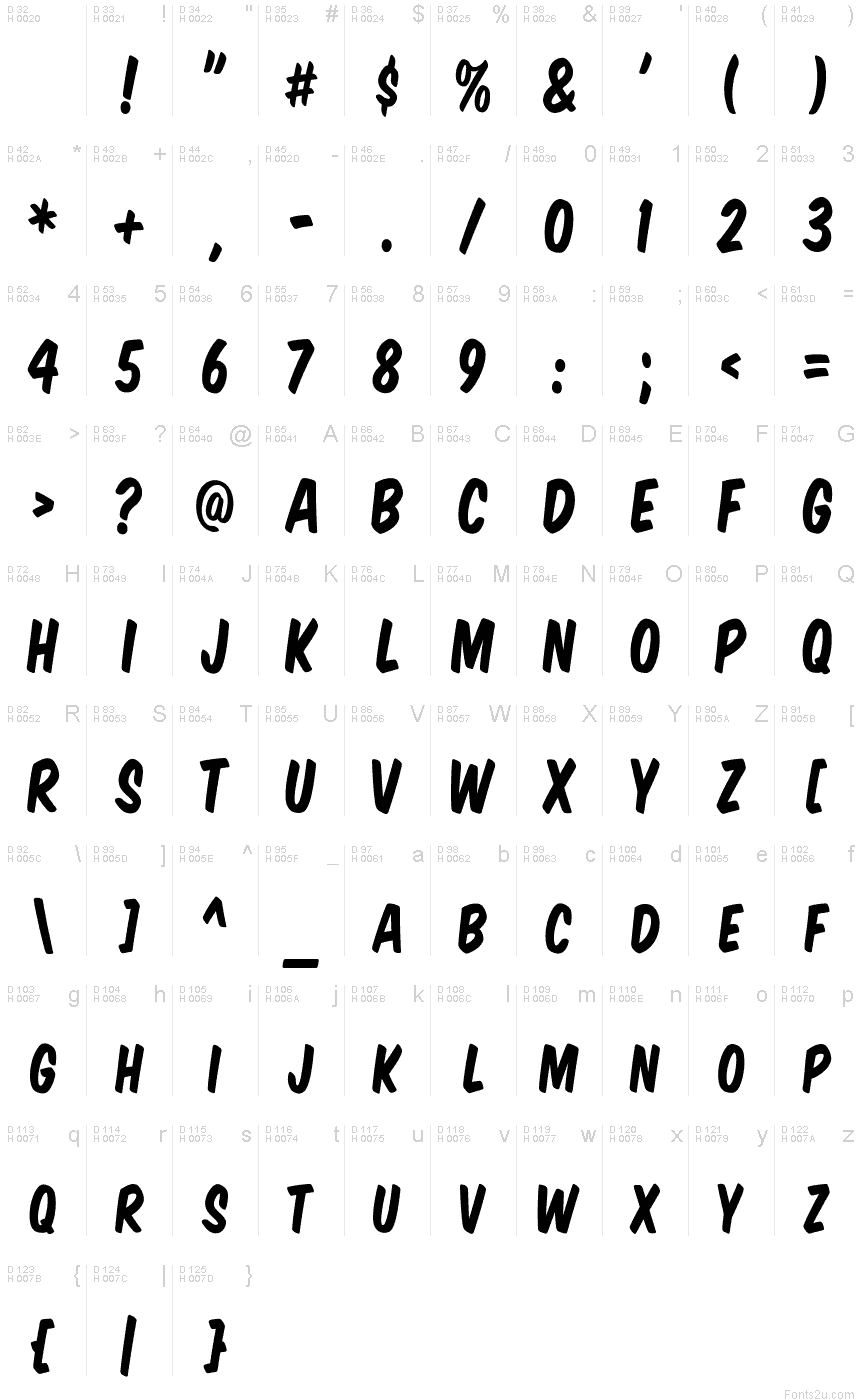
VTC Super Market Sale SC od VTC Vigilante Typeface Corporation je bezplatné písmo v komiksovém stylu s výrazným, ručně malovaným nádechem, který evokuje akční cedule a nápisy ve výlohách. Písmena mají hrubé, nepravidelné tahy, zúžené křivky a skákavou šířku, takže působí, jako by byla rychle nahozená štětcem, nikoliv pečlivě vysázená.
Skvěle se hodí na plakáty, letáky, výprodejové bannery, cenovky, obaly na svačiny a hravé titulky, kde syrový styl obchodních výloh pomáhá nastavit tu správnou atmosféru. Jako font zdarma funguje výborně i pro krátké texty na obálkách a monogramy, protože přehnané velké znaky dodávají spoustu charakteru, aniž by zabíraly příliš místa.